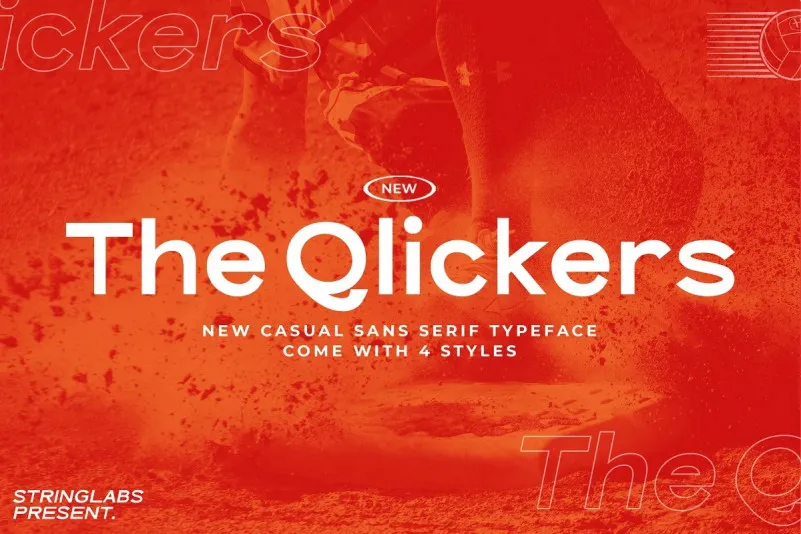
The Qlickers Sans Serif Font Family – Download Grátis
A fonte The Qlickers Sans Serif é uma elegante tipografia humanista com dois estilos e quatro pesos. Ela foi criada e compartilhada pela StringLabs, destinando-se a um vasto leque de usos como posteres para filmes, headlines, letras em bloco, subtítulos de logotipos e muito mais. Com seu design cuidadosamente profissional, esta fonte é uma ótima escolha para qualquer projeto que exija estilo moderno e clássico. Seja para personalizar posters de cinema ou construir um logotipo memorável, The Qlickers Sans Serif está a sua disposição. Sua simplicidade e elegância tornam-na uma excelente opção para adicionar um toque único ao seu projeto gráfico.